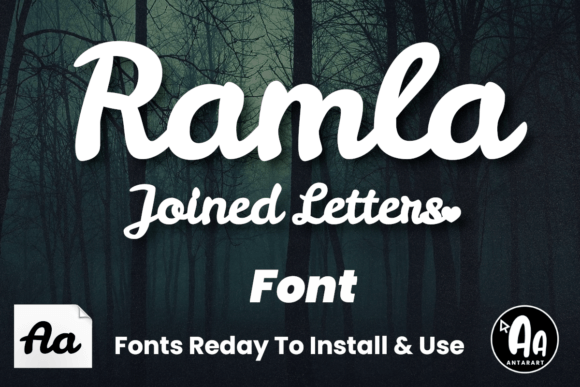
Ramla
Jika Anda mencari aset berkualitas tinggi seperti Ramla, paket premium ini adalah pilihan fantastis untuk proyek kreatif Anda.
Baik Anda membuat produk POD (Print on Demand), undangan pernikahan, atau grafis media sosial, Ramla adalah pilihan yang sangat ideal.